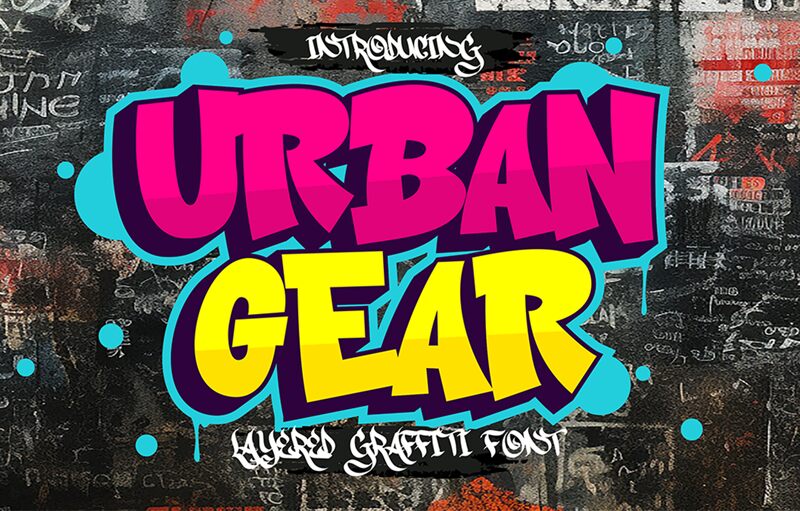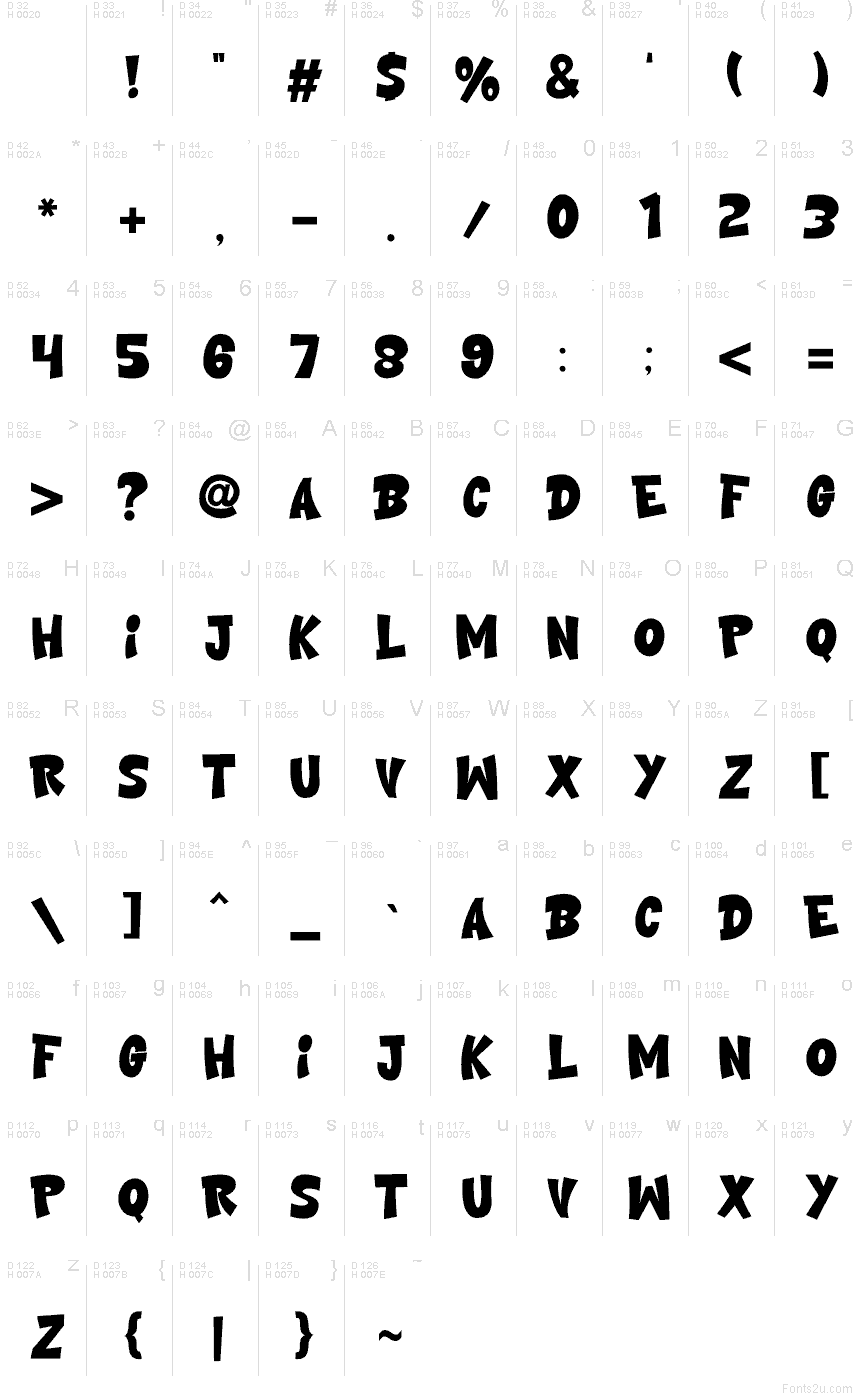
Urban Gear od CikareotypeStudio je bezplatné komiksové písmo typu display, tvořené velkými, nakloněnými tvary, které působí, jako by byly vystřiženy z měkkého černého papíru. Tento nerovnoměrný rytmus s poskakujícími horními okraji a lehce zúženými vnitřními prostory dodává písmu výrazný plakátový nádech, daleko od úhledné kreslené předlohy.
Pro plakáty na mládežnické akce, obaly na snacky, nadpisy v arkádovém stylu, miniatury na YouTube nebo streetwearovou grafiku má Urban Gear dostatečný švih, aby okamžitě ukotvil krátká slova. Jeho lehce nepravidelná silueta zabraňuje tomu, aby nadpisy působily staticky, což z něj dělá ideální volbu všude tam, kde chcete hravější a dynamičtější vzhled.